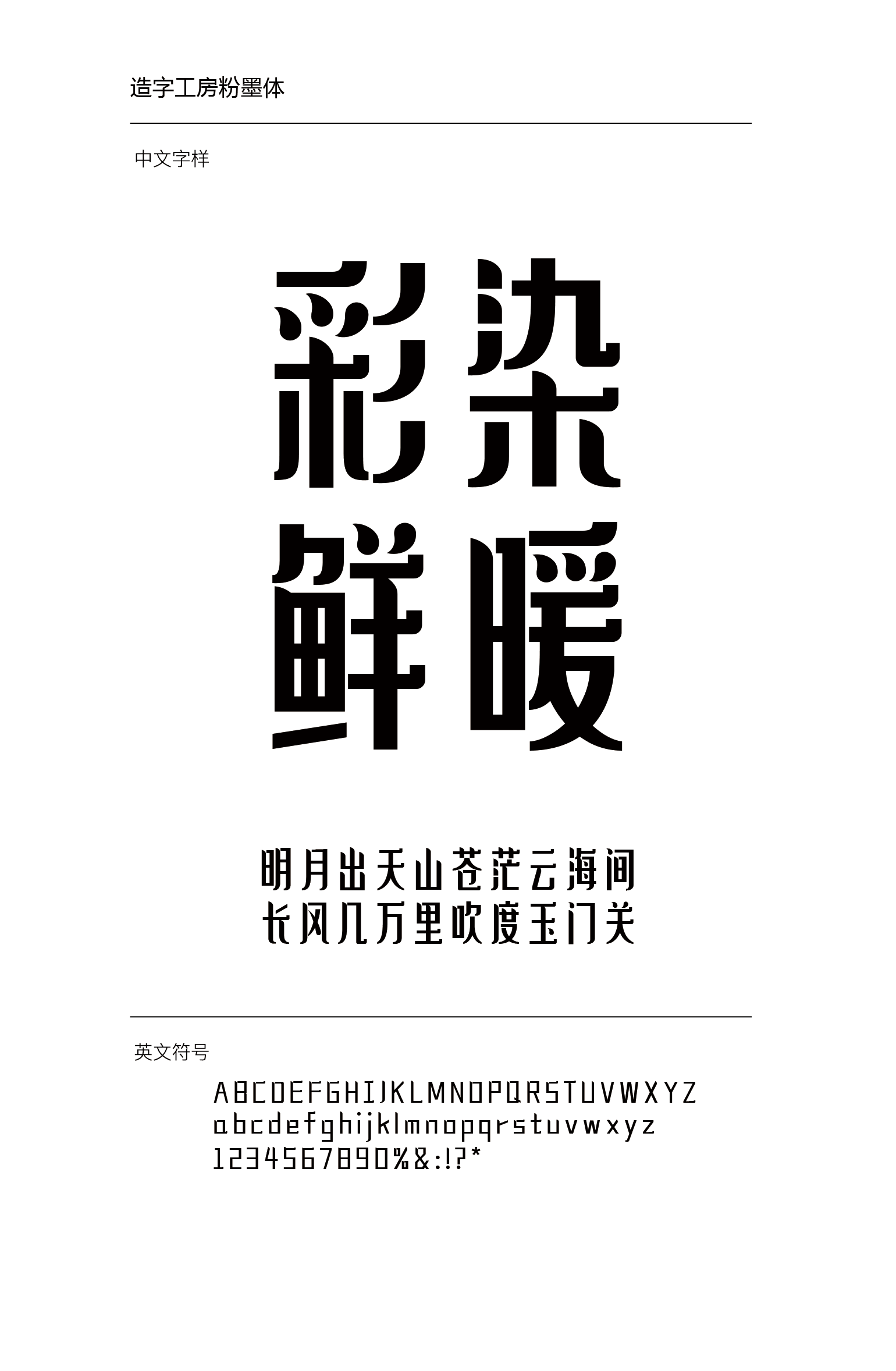
造字工房粉墨体设计说明
造字工房粉墨体,其字修长、平和工稳,结构紧密,俊秀飘逸,字形中弧角的巧妙应用,令字体平添几分柔和雅致、粉墨雍容之感,局部特点的处理细腻丰富,整体风格收放有度、清雅秀媚,引人注目,适用于大标题、品牌广告宣传等需要强力视觉表现的环境。本字体为简体字库,采用OpenType/CID格式,Adobe-GB1-5编码。基于中华人民共和国GB2312-80字符集标准,另按需添加101个汉字。共收容字数6864CJK汉字,ASCII常用字符100个。